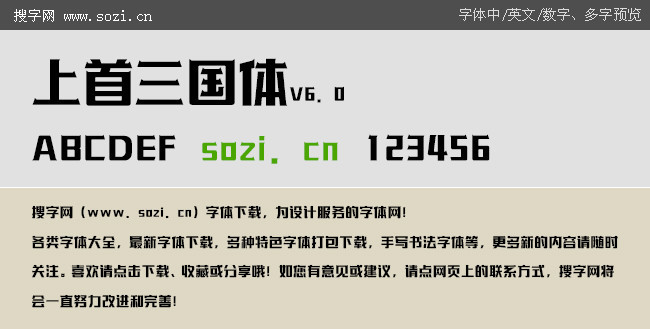
上首三國(guó)體V6.0
搜字網(wǎng)給大家提供一款上首三國(guó)體中文字體下載,上首三國(guó)體其字形遒勁剛健,特點(diǎn)處做尖角處理,令其鋒芒畢露,剛毅果敢,方正沉穩(wěn)又不失大氣(此版本為升級(jí)版本)。適用于搭配標(biāo)志、廣告標(biāo)語(yǔ)、商業(yè)廣告等廣告設(shè)計(jì)。